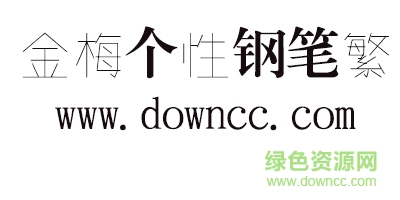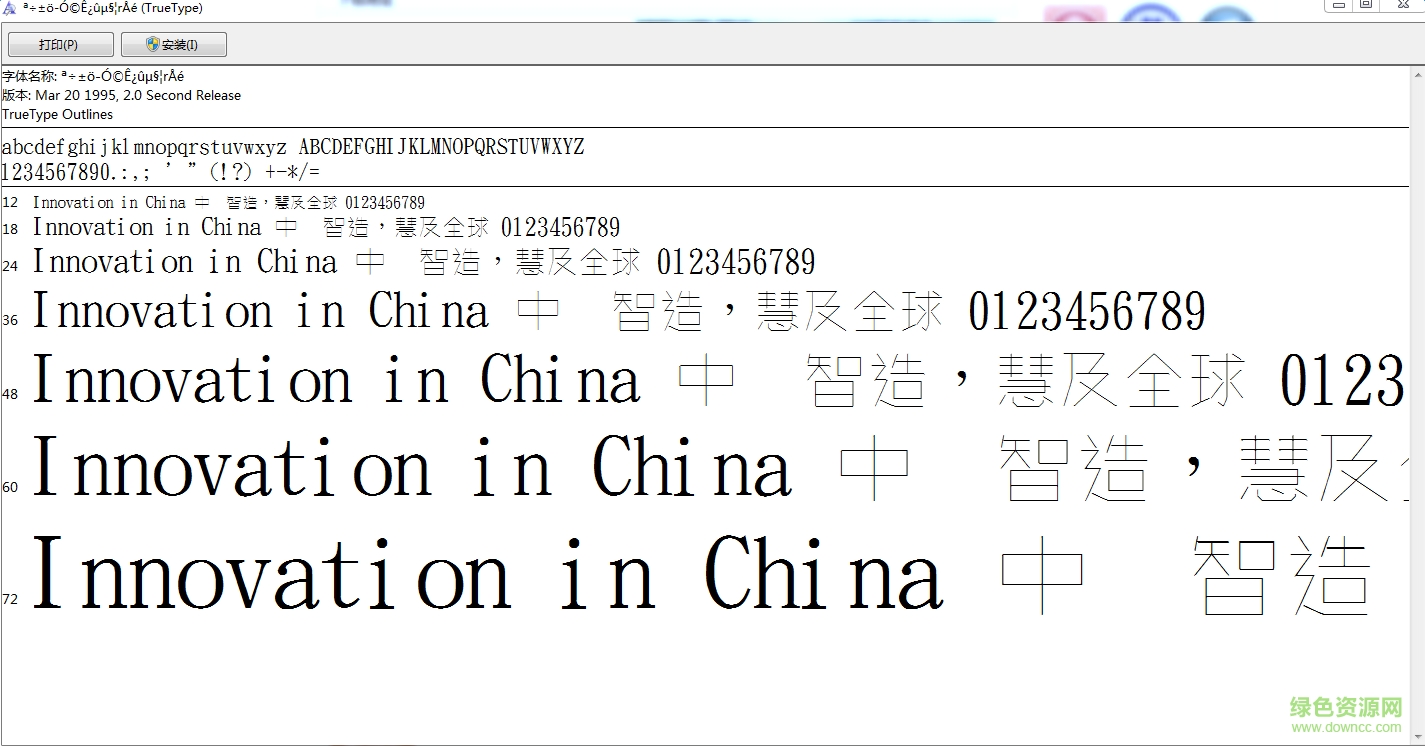
金梅個(gè)性鋼筆字體具有結(jié)構(gòu)美、線條美、風(fēng)格美的特點(diǎn)。鋼筆字體看起來非常娟秀有靈氣。很受一些書法家的喜愛!同時(shí)也可以應(yīng)用于印刷設(shè)計(jì)、廣告設(shè)計(jì)等行業(yè)!歡迎下載使用。
金梅個(gè)性鋼筆字體是一款非常獨(dú)特的金梅繁體字體,線條纖細(xì),字形優(yōu)美,適用于廣告、美工、海報(bào)等各種設(shè)計(jì)領(lǐng)域,喜歡這款字體的朋友快來綠色資源網(wǎng)下載吧。